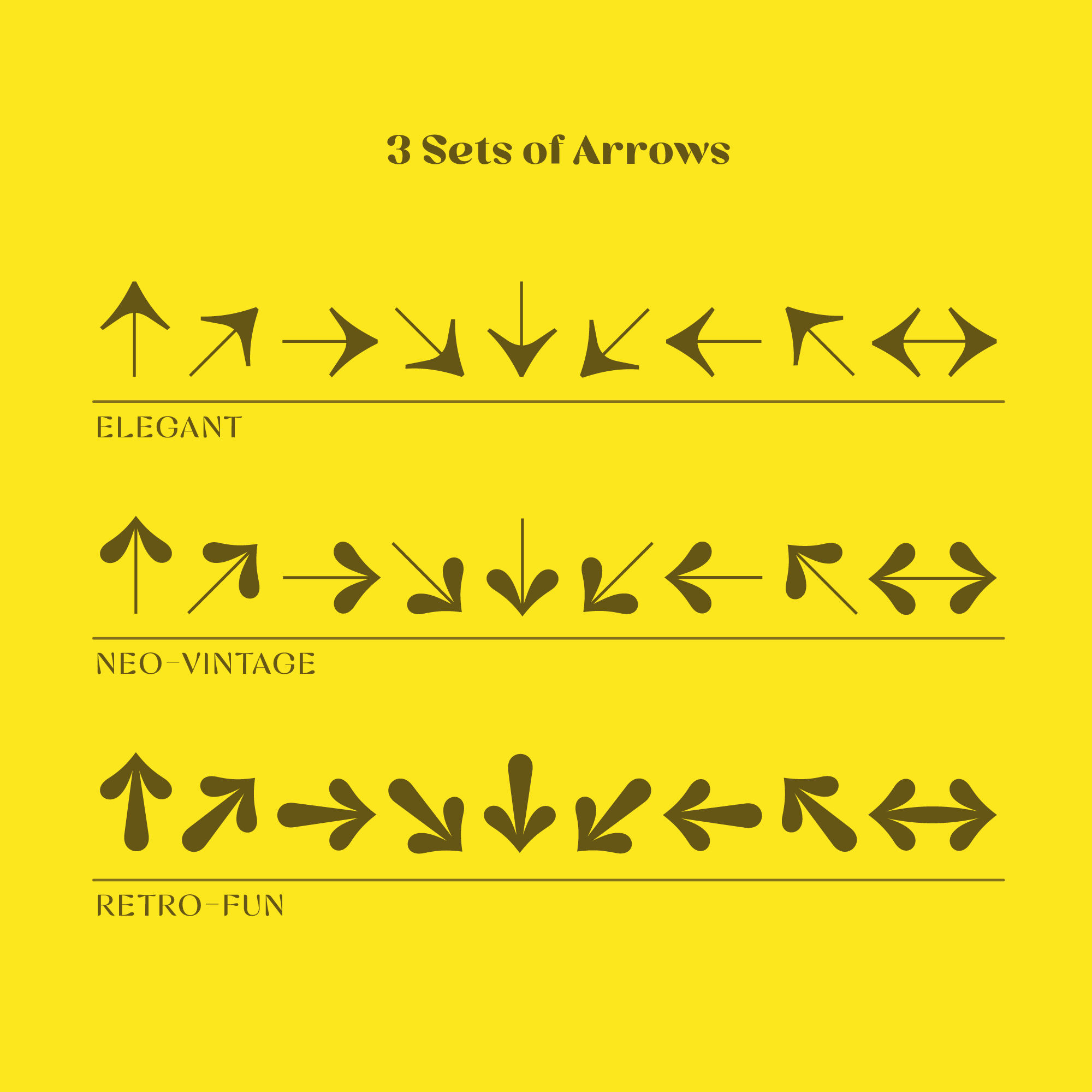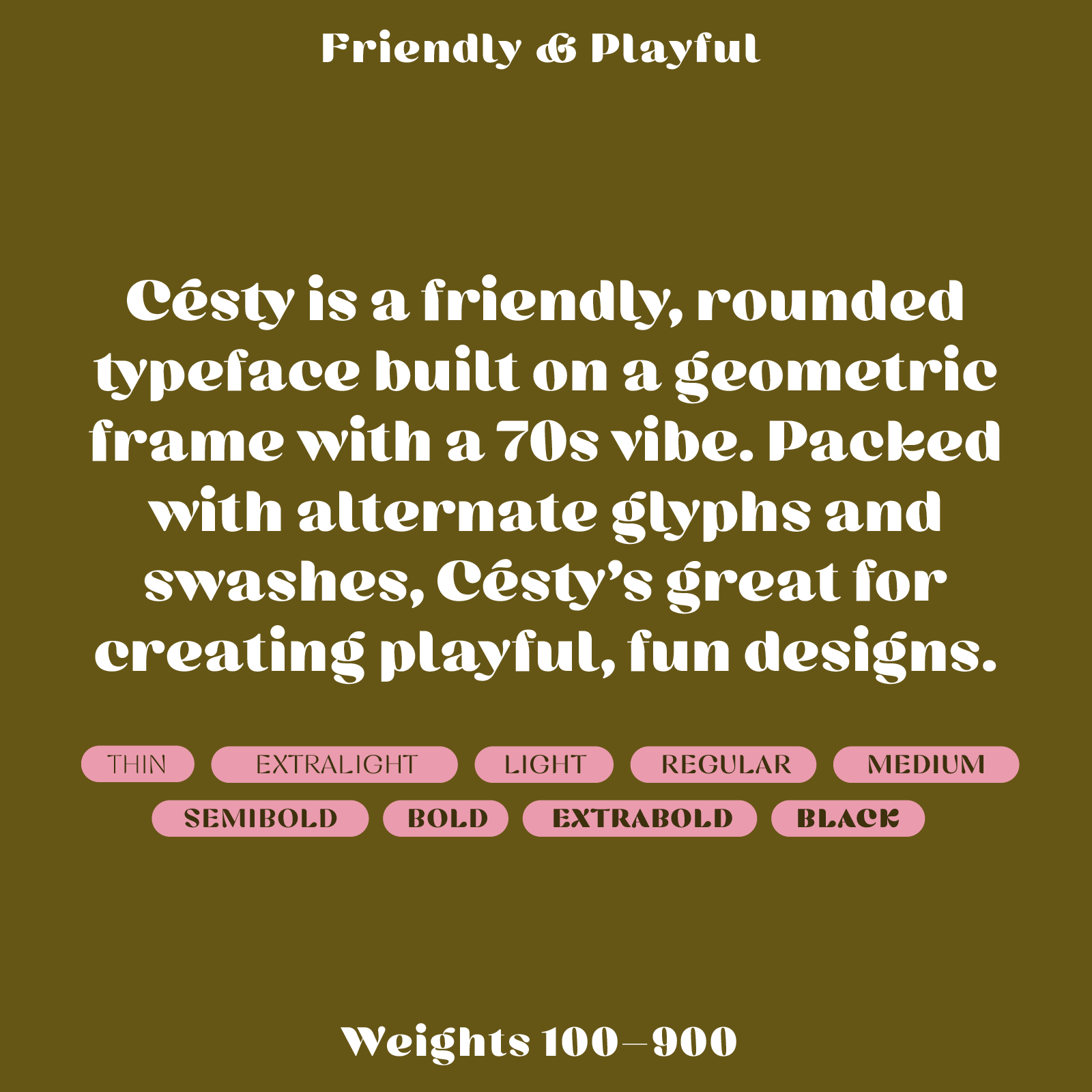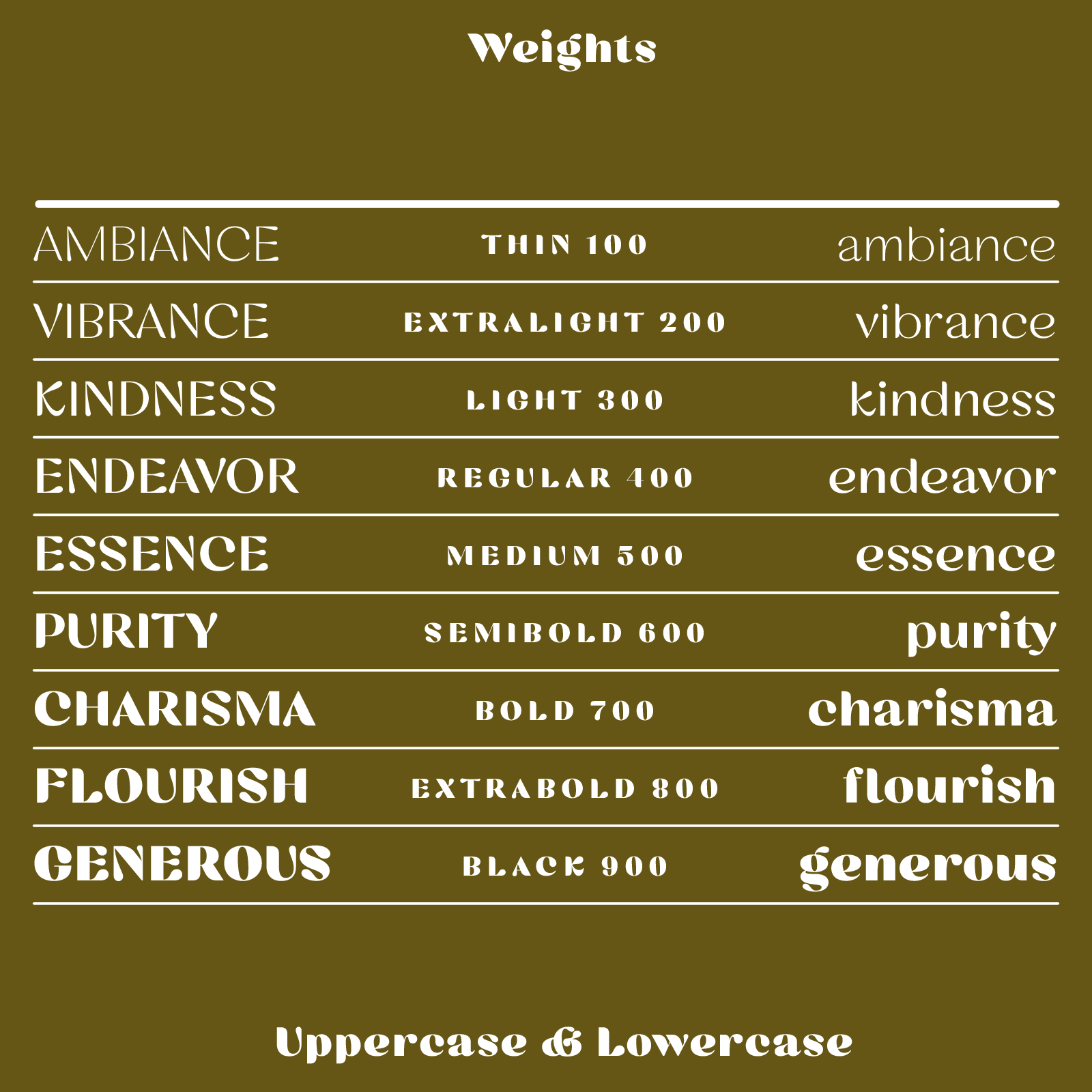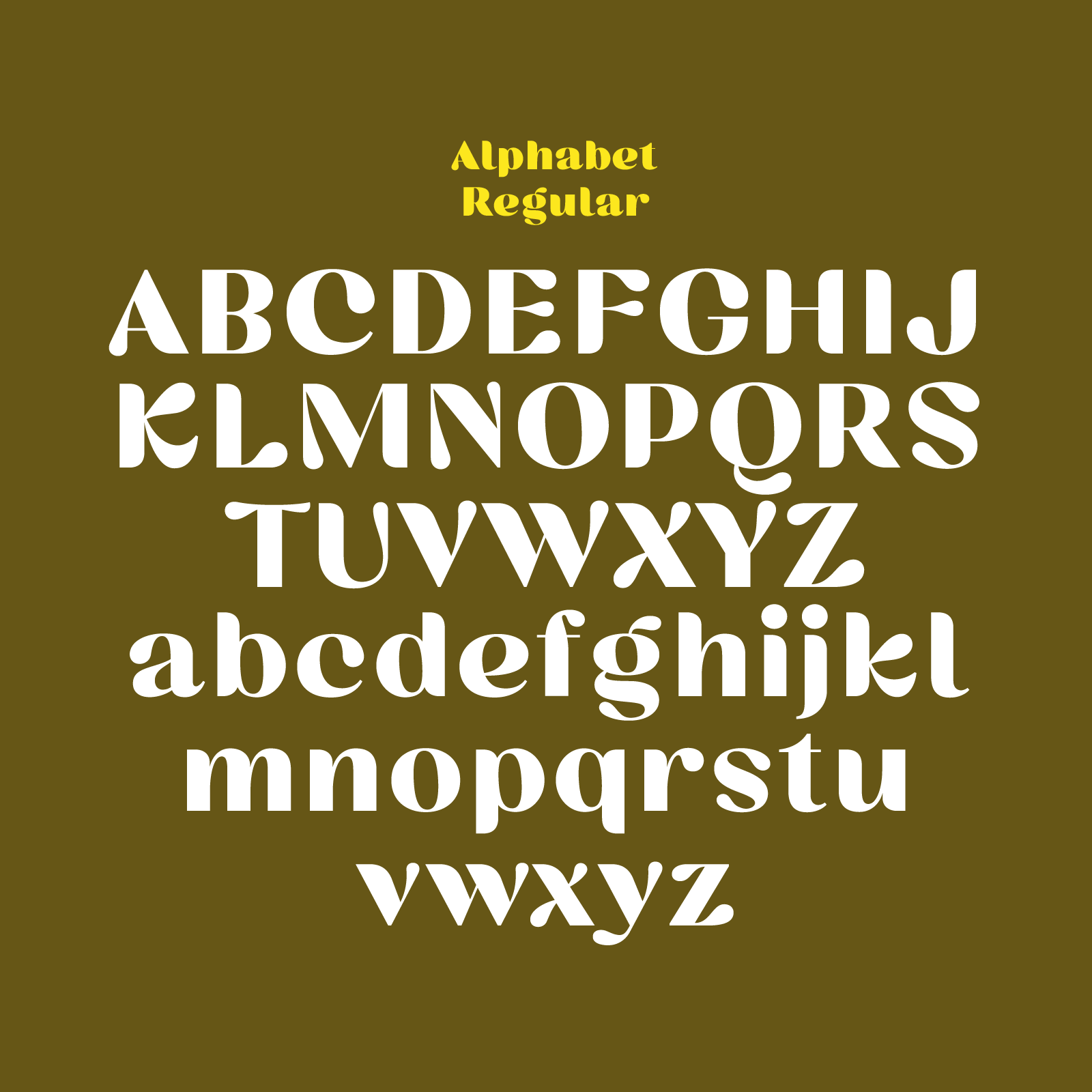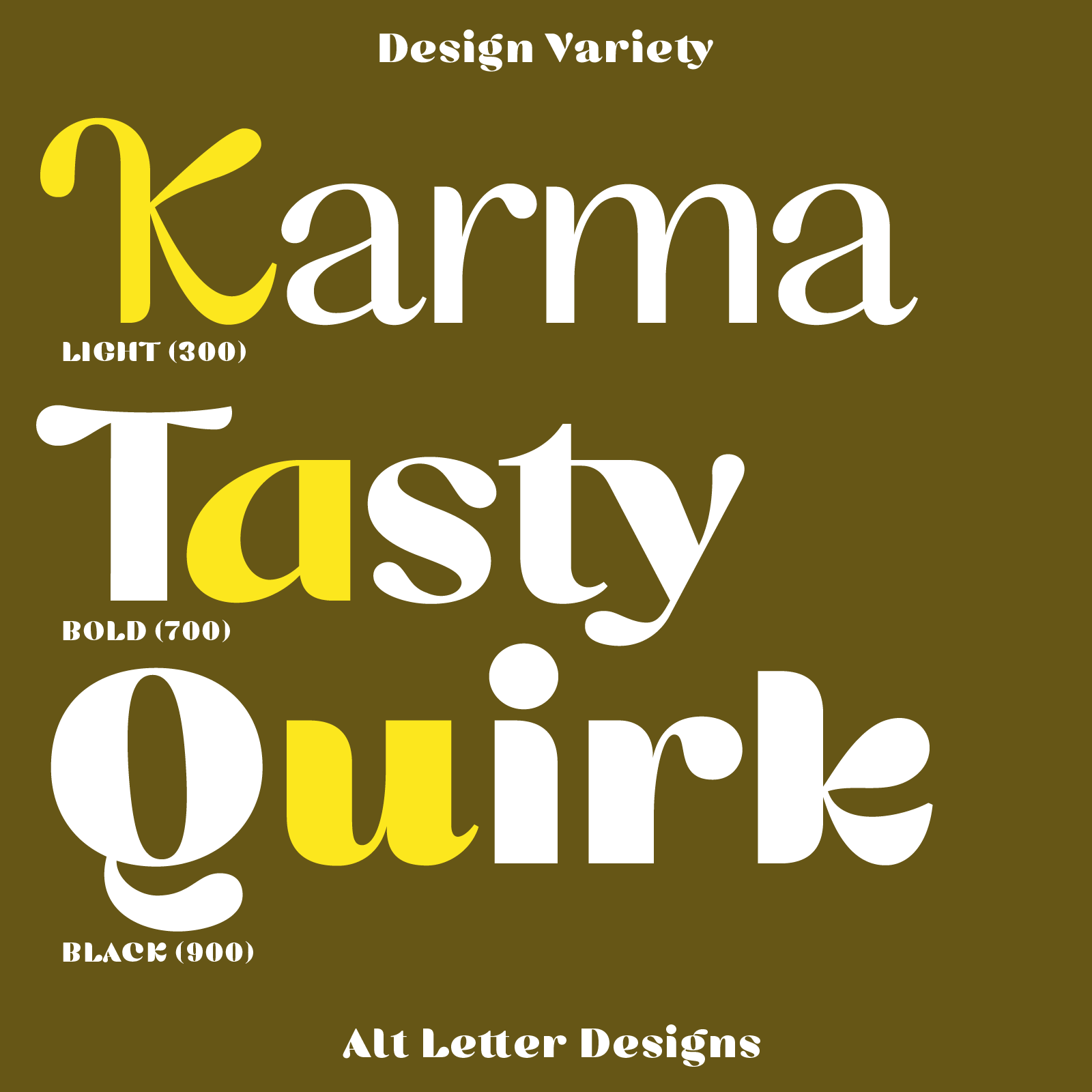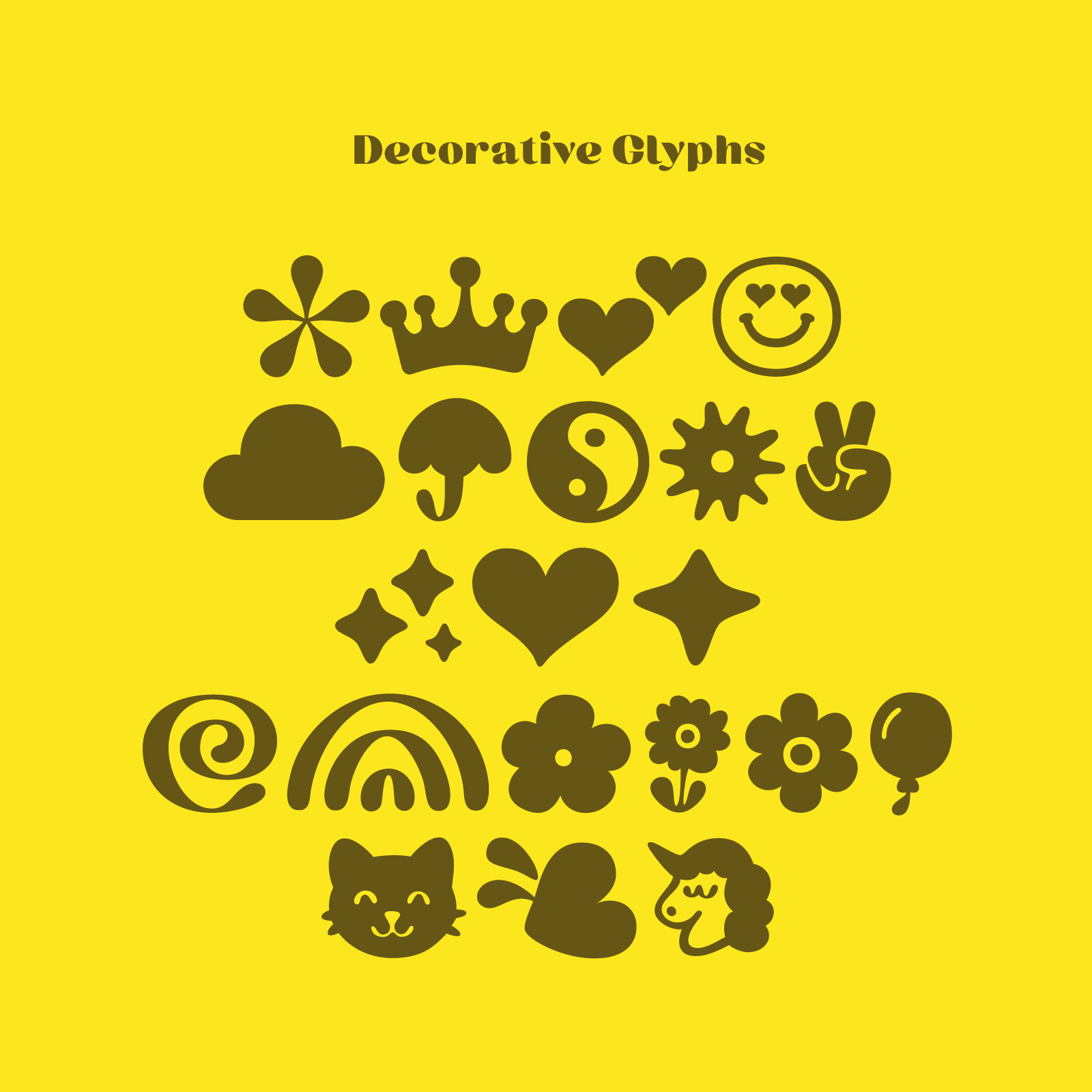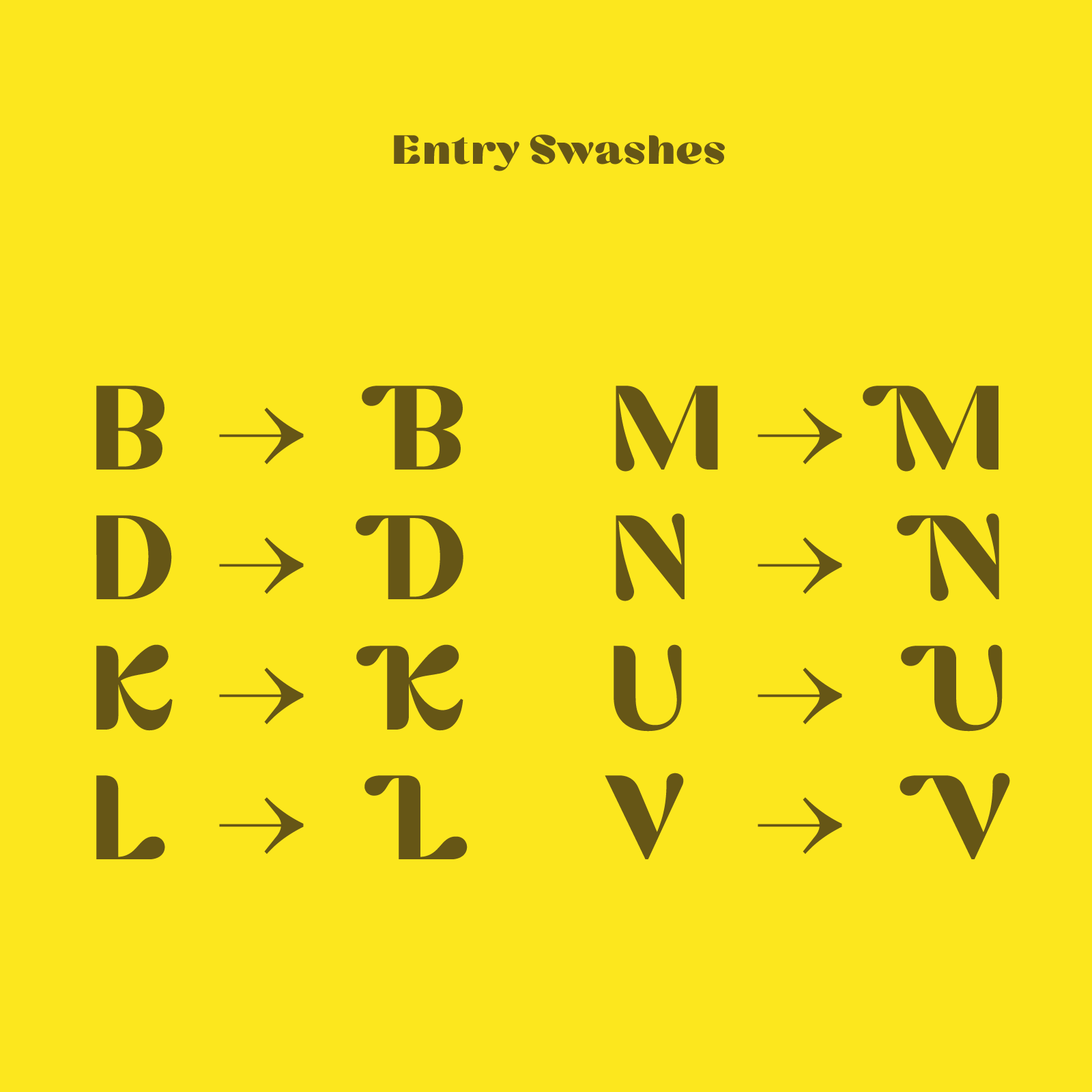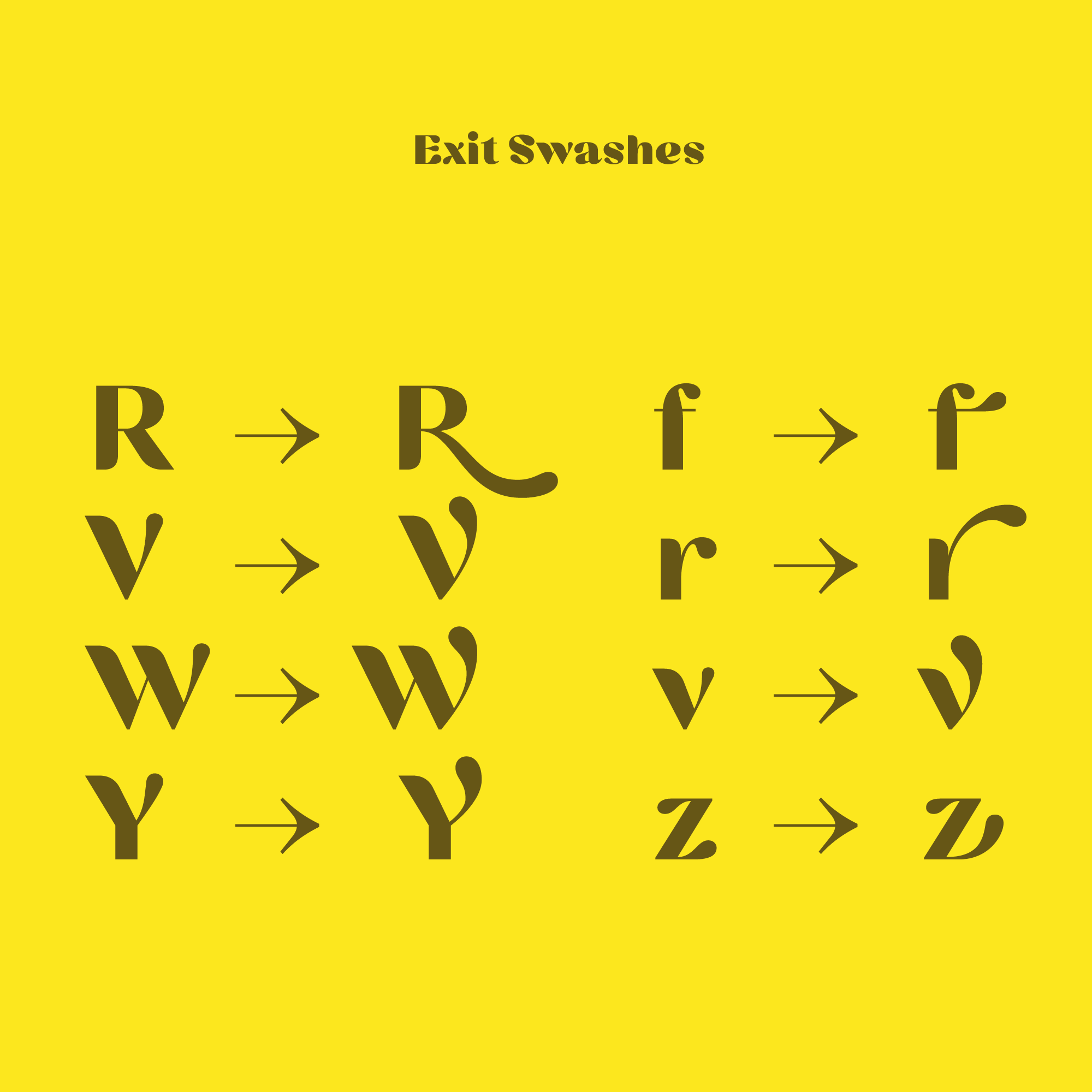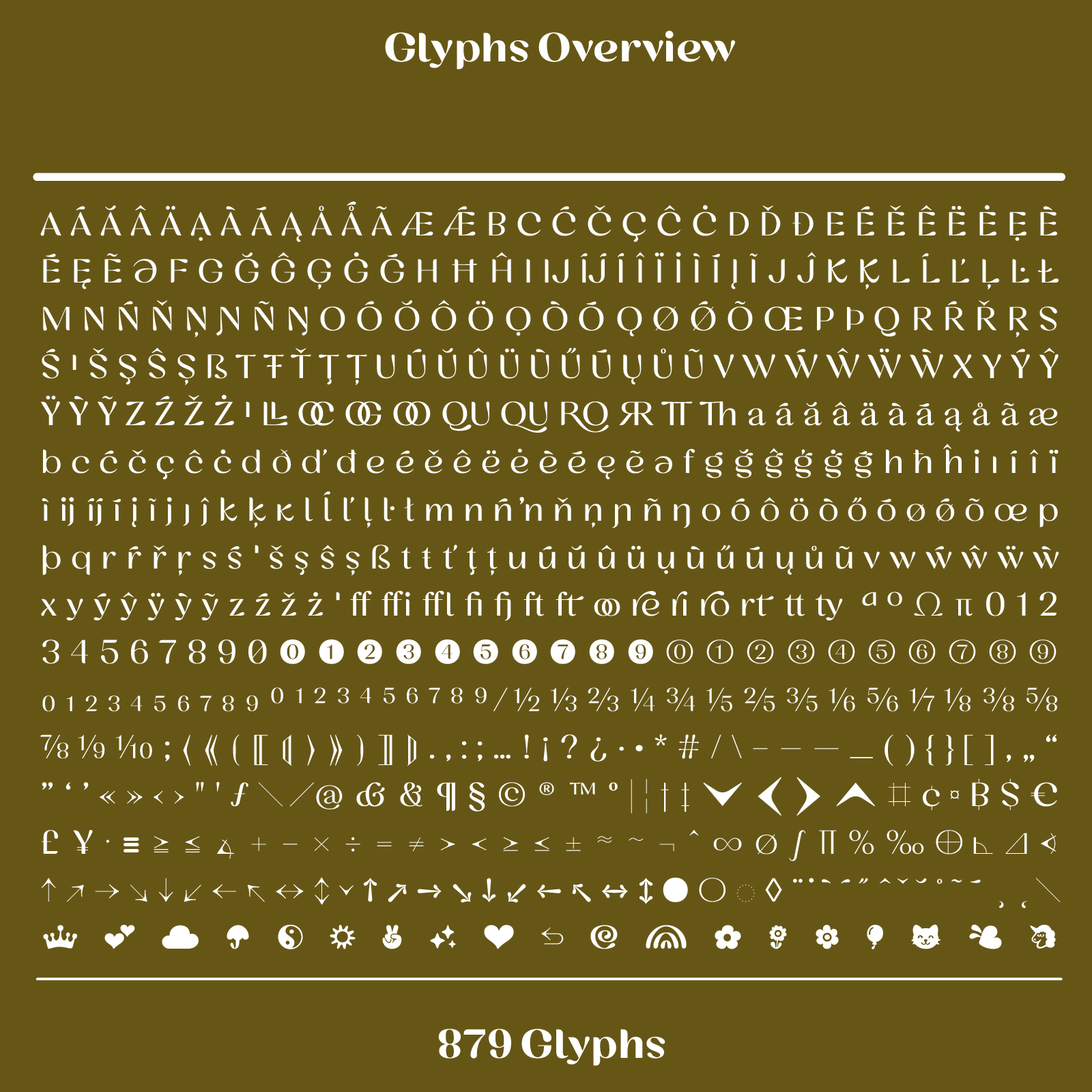
Cesty, modern 70s fonts
Cesty: Freundliche, runde Display-Schrift für Logos und Verpackungen
Kräftig, rund und zugänglich.
Cesty ist eine kräftige, runde Display-Schrift mit freundlicher Ausstrahlung. Die fetteren Schnitte haben eine weiche, volle Form, die leichteren wirken offen und federnd. Passt gut zu Logos, Postern, Verpackungen, Gaming-Grafiken, Speisekarten und Marken, die kräftig, aber zugänglich auftreten wollen.
Cesty · variabel, 100 bis 900
9 + VFSchnitte, Thin bis Black, plus eine variable Datei
897Glyphen
12Stilsets
LatinWest- und Mitteleuropäisch
Cesty ist eine moderne 70er-Schrift mit Blasen-Endungen, die dennoch bei geometrischen Formen bleibt.
Dicke Rundungen, dünne Verbindungen und gerundete, spitz zulaufende Enden. 3 und 5 enden in Kugelenden.
Die leichten Schnitte wirken offen und federnd, Black schließt die Punzen zu Schlitzen. Swash-Großbuchstaben und je vier Varianten von a und g für Logos, Plakate, Verpackungen und Speisekarten.
Cesty im Detail
Am besten für
Logos, Plakate, Verpackungen, Speisekarten und Spielegrafik; eine Display-Schrift für Headlines und Namen.
Passt zu
Familie
9 Schnitte, Thin bis Black, dazu eine variable Schrift. 897 Glyphen, 12 Stilsets.
Sprachen
Lateinisch, Westeuropäisch, Mitteleuropäisch.
Ziffern
Proportionalziffern, Tabellenziffern, Null mit Schrägstrich.
OpenType
Satzzeichen für Versalien, bedingte Ligaturen, Brüche, Standardligaturen, Ordinalzeichen.
Ligaturen
ff fi ffi ffl fj ft tt ty TTstandardmäßig aktivTh gi oo OO OC OG QU RO RR LL re ri ro rtbedingt, im Programm einschalten